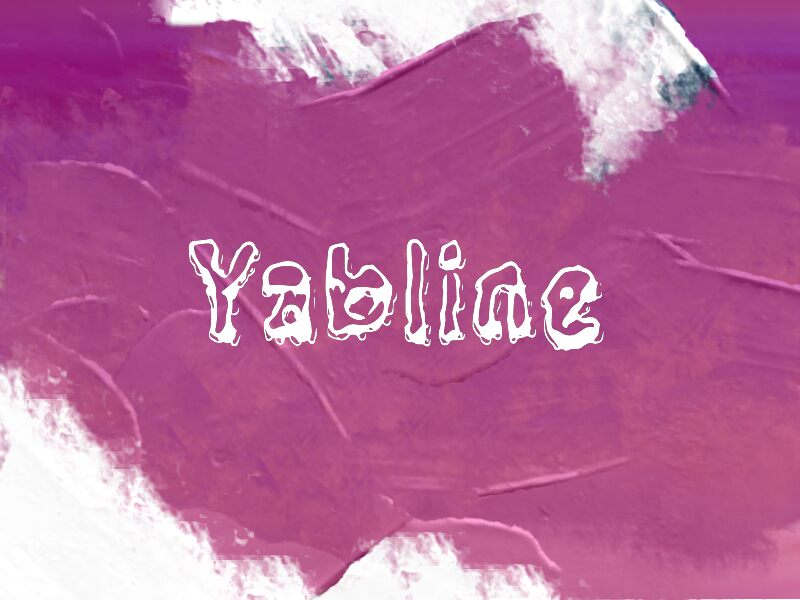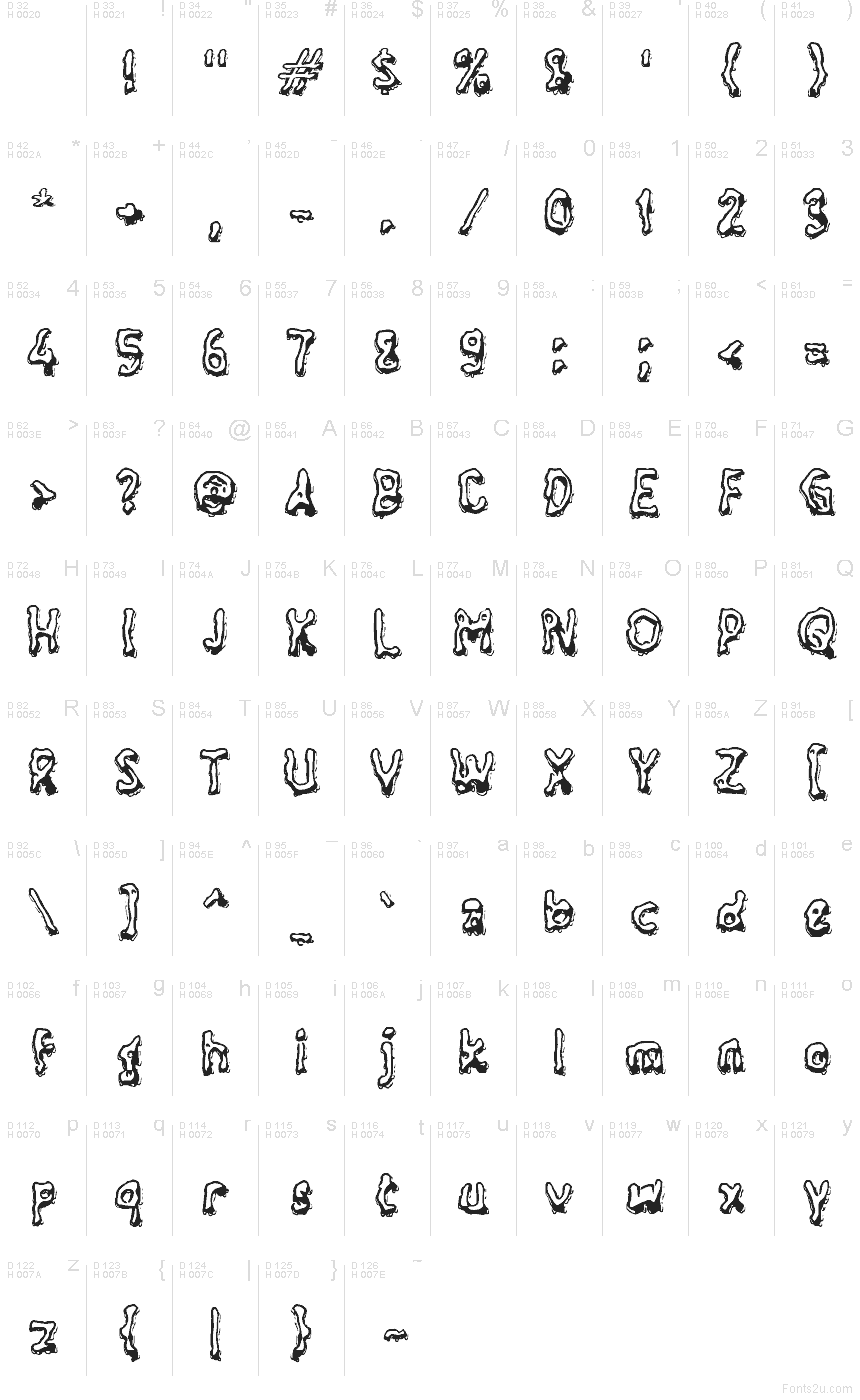
Yabline
Yabline por Wep é uma fonte display decorativa e gratuita, moldada por contornos escorridos e irregulares que dão a cada letra um aspecto levemente derretido. As ondulações repetidas, as gotas pendentes e os espaços internos irregulares conferem ao design um ritmo viscoso, que parece intencional em todo o conjunto, fugindo daquele visual de desgaste aleatório.
Essa textura escorregadia combina perfeitamente com flyers de Halloween, convites para festas temáticas, títulos de jogos, embalagens diferenciadas e posts nas redes sociais que pedem um título orgânico e estranho. Palavras curtas e títulos grandes são os mais beneficiados, já que os contornos caídos e as formas de mancha transformam o texto simples em um elemento gráfico impactante, em vez de um título neutro.